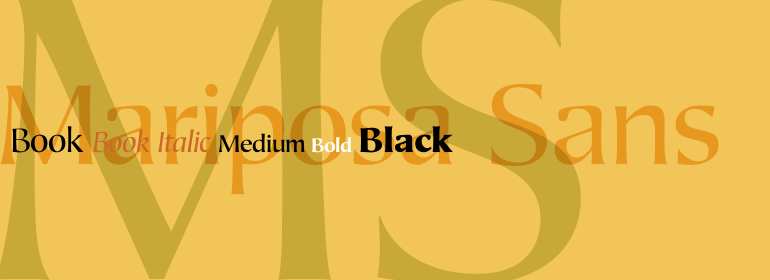
Mariposa Sans™
Mariposa Sans™,这款字体结构工整、笔画清晰,兼顾美观与易读性,适用于标题、正文、海报、包装、LOGO 等多种场景。字形优雅稳定,风格百搭耐看,适配日常排版与创意设计,让文字呈现更舒适、更具质感。Mariposa Sans™一笔一画,皆是细节,以均衡的比例、流畅的线条打造舒适视觉体验,字形端正大气,风格简约现代。无论是商业设计、品牌宣传还是日常排版,都能轻松驾驭,让文字更有格调与力量。Mariposa Sans™字体下载。
字体品牌: ITC(Monotype) 设计师:Bouwsma,Philip 字体分类:无衬线体 字体属性:外文 字符集:Unicode 发布时间: 2018